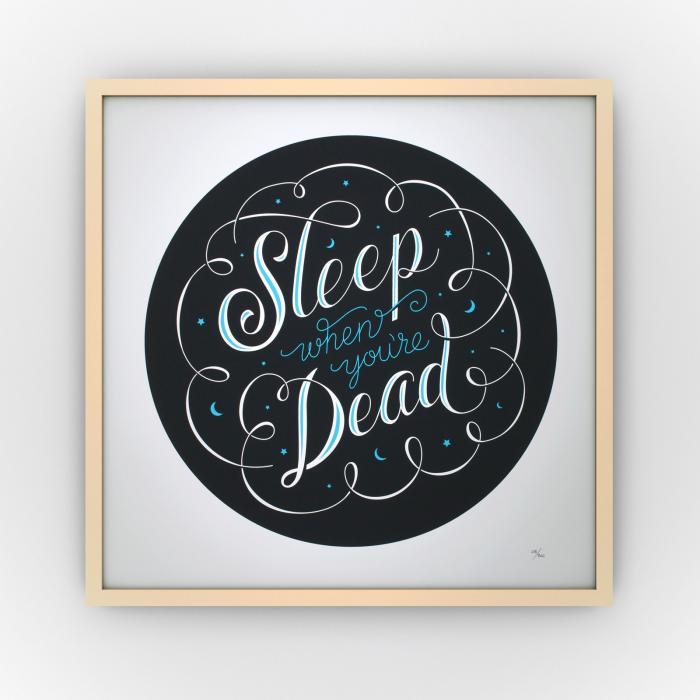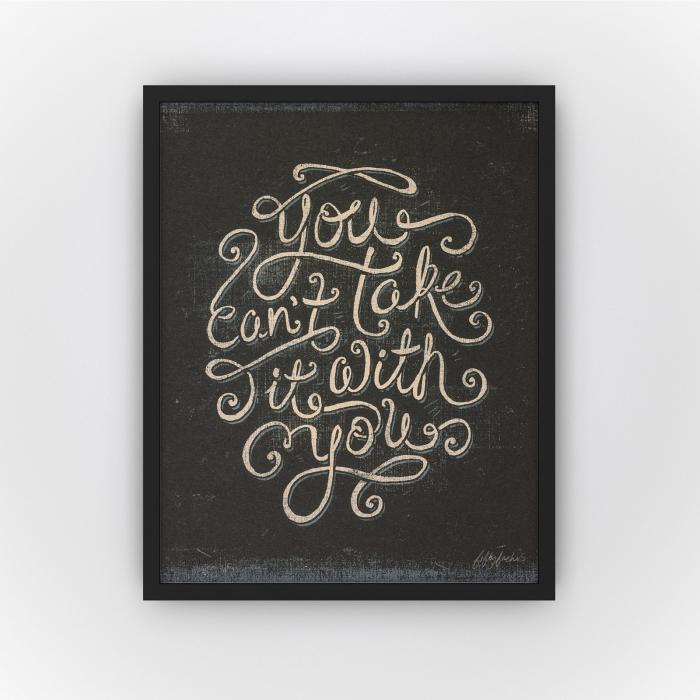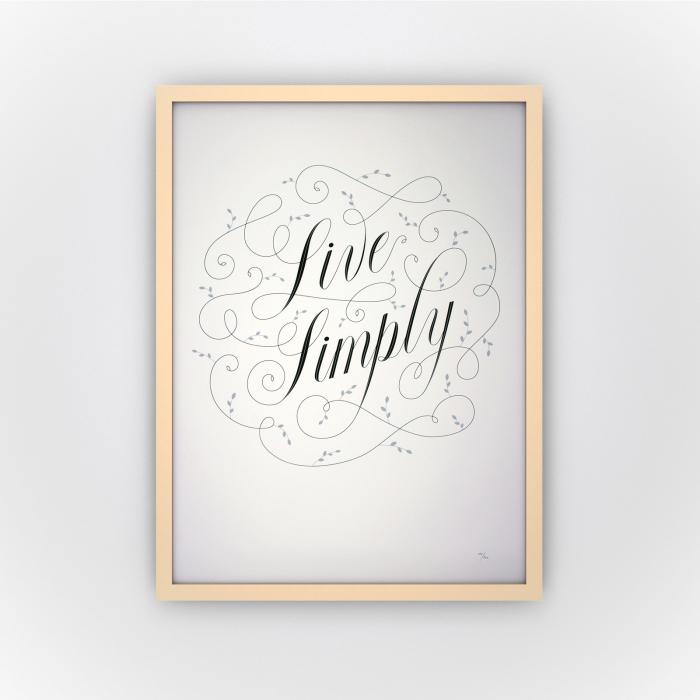
Kalligraphie-Stil gesucht
ich bin auf der Suche, wie man den Typo/Design-Stil nennt, wenn man die Schrift in so nette Verästellungen einbindet. Schwer zu erklären was ich meine, dazu die angehängten Dateien.
Ich weiß, dass ist nicht die feine englische Art danach zu fragen, aber sollte es im Netz ein Generator dafür geben, immer her damit, bitte :D
Ich muss nämlich die Worte "White Trash" in sowas einbinden und kanns einfach nicht.
Das ist ja gerade die Kunst: Dass das eben nicht jeder mal so zwischendurch macht  8-)
Es ist einfach so, dass der Computer einigrs kann, aber letztlich immer nur ein weiteres Werkzeig in der Hand eines K
ünstlers bleibt - was ja auch gur so ist, sonst werden so manche Dinge schnell zu einer toten Massenware.
Will man so etwas auf die Beine stelklen, braucht man also 3 Dinge:
1.  das entsprechende Talent
2., das richtige Werkzeug
2. das Wissen, wie man das Werkzeug dann anwendet.
Das erste muss man haben, das 2. kann man kaufen und das dritte kann man lernen, z.B. in einem Kalligrafie-Kurs.
Ich finde Talent wird immer überbewertet und würde es hier (oder generell) durch Interesse/Motivation ersetzen. Ein einfacher Kalli-Kurs wird einem dabei auch nicht viel helfen, es braucht schon einige Übung* um etwas brauchbares hinzubekommen – und da kommt wieder die Motivation für das Durchhaltevermögen ins Spiel ...
* Mein Kalli-Dozent hat immer gesagt, man muss mindestens 5 km in einer Schrift schreiben um sie halbwegs zu beherrschen  :tutor:
So etwas kann man schon am Rechner zusammenbasteln. Das Werkzeug dafür muß man nicht unbedingt kaufen, das kostenlose Inkscape kann es auch. Talent wäre nett. Aber das Wissen wie man das Programm nutzt ist schon notwendig.
In Inkscape kann man seit einiger Zeit sogenannte Spiro splines erzeugen, damit kann man recht schöne Spiralen und Schwünge erstellen. Allerdings sind diese Kurven etwas eigenwillig und bisweilen schwer zu bändigen. Hier mal ein, leider englischsprachiges Video in welchen die Funktion erklärt wird. Man kann diese Kurven auch an Schriften ansetzen, im Muster an die FlemishScript BT.
Wenn dies zu umständlich ist, kann man auch fertige Schriften mit Ornamenten nutzen, bei Intellecta Design gibt es z.B. einige davon – zumeist kostenlos für den Privatgebrauch. Allerdings setzen diese dann aber nicht an die Schrift an. Auch die Opattfram01 und die FoglihtenFr02 beide kostenlos von Glukfonts bieten interessante Rahmen. Man kann ja in die Rahmen der FoglihtenFr02 auch eine andere Schrift hereinsetzen.
P.S.: Muß man solch einem Unwort einen so schönen Rahmen geben? Davon wird es auch nicht besser!
Hmmm, vergleicht man jetzt mal sein Beispiel, das anscheinend in einer halben Stunde entstanden ist, mit den Beispielen im Ausgangspost, sehe ich aber einen meilenweiten Unterschied ...
Und wenn man das noch mit Schrift kombinieren will, ist das nicht mal eben hingedängelt (vor allem, wenn’s vernünftig aussehen soll). Dieses Spline-Tool sieht ja erstmal nach einer tollen Sache aus – die Frage ist nur, ob das nicht nur eine schöne Spielerei ist und wenn man weiß, was man will und Erfahrung mit derartiger Gestaltung hat, man dann nicht doch eher den üblichen Weg geht, weil man da einfach mehr Kontrolle hat.